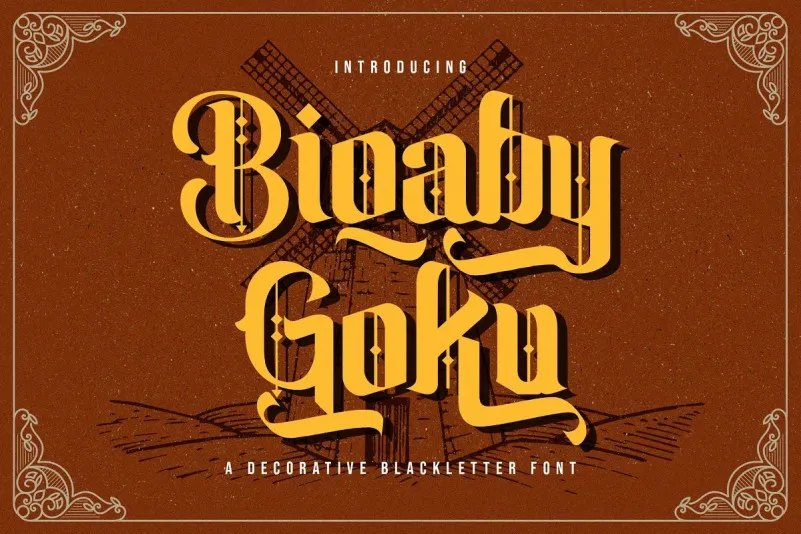
A Biqabygoku Font é uma herança do tipo tipográfico Blackletter que remonta ao entusiasmo pelo design de rótulos fashion dos anos 70 até a contemporaneidade. Desenvolvida e compartilhada pela StringLabs, esta fonte Gothic destaca-se por trazer o olhar moderno da estética visual à tipografia clássica. Ela é perfeita para complementar seus projetos criativos, tornando-os ainda mais impactantes e distintos. Em seu estado de demo, a Biqabygoku Font é gratuita para uso pessoal; já no formato completo e comercial, visite aqui para obter mais opções. Para aqueles que valorizam tanto a estética clássica quanto as últimas tendências da moda visual, esta fonte é uma ótima escolha.